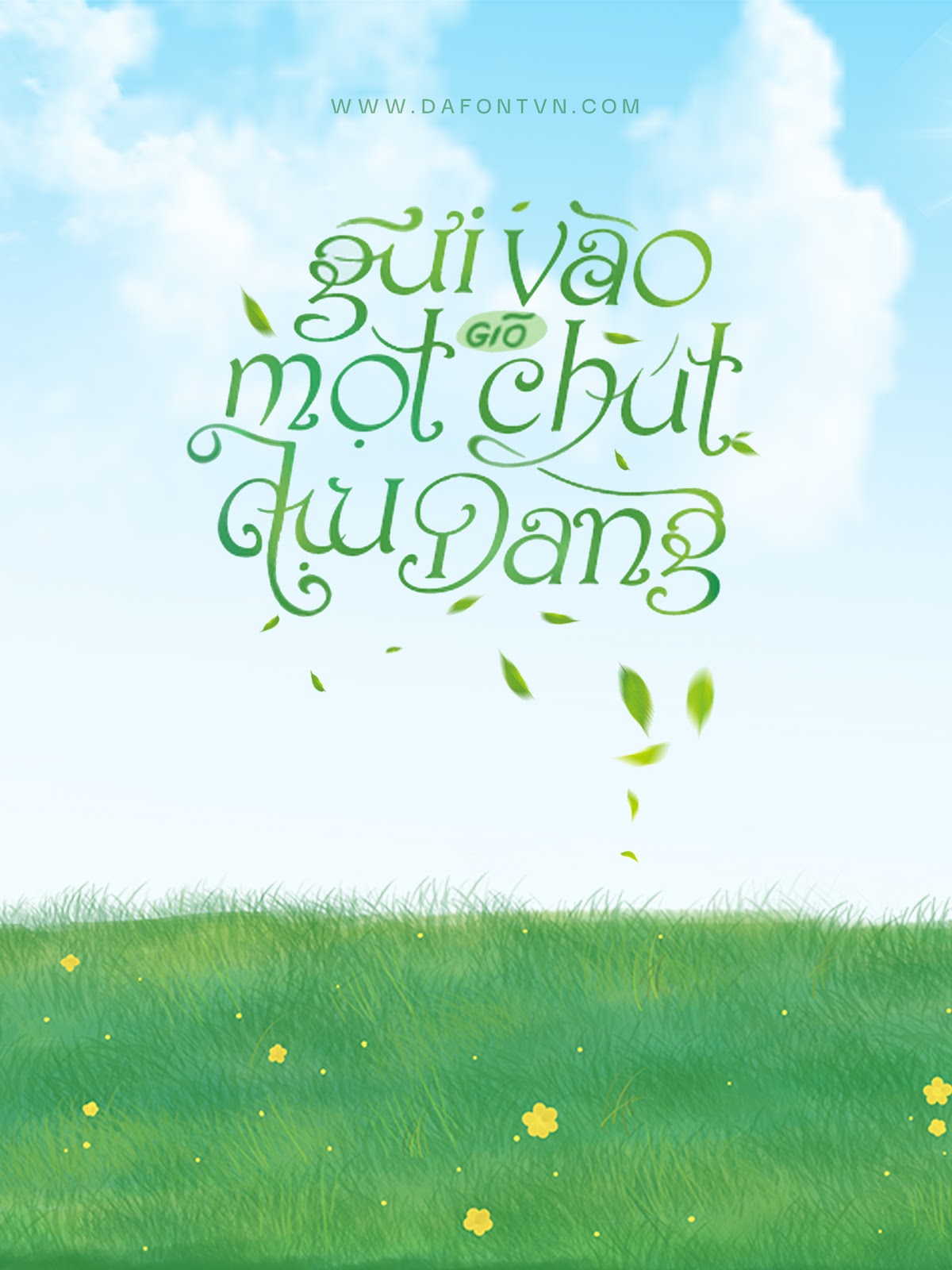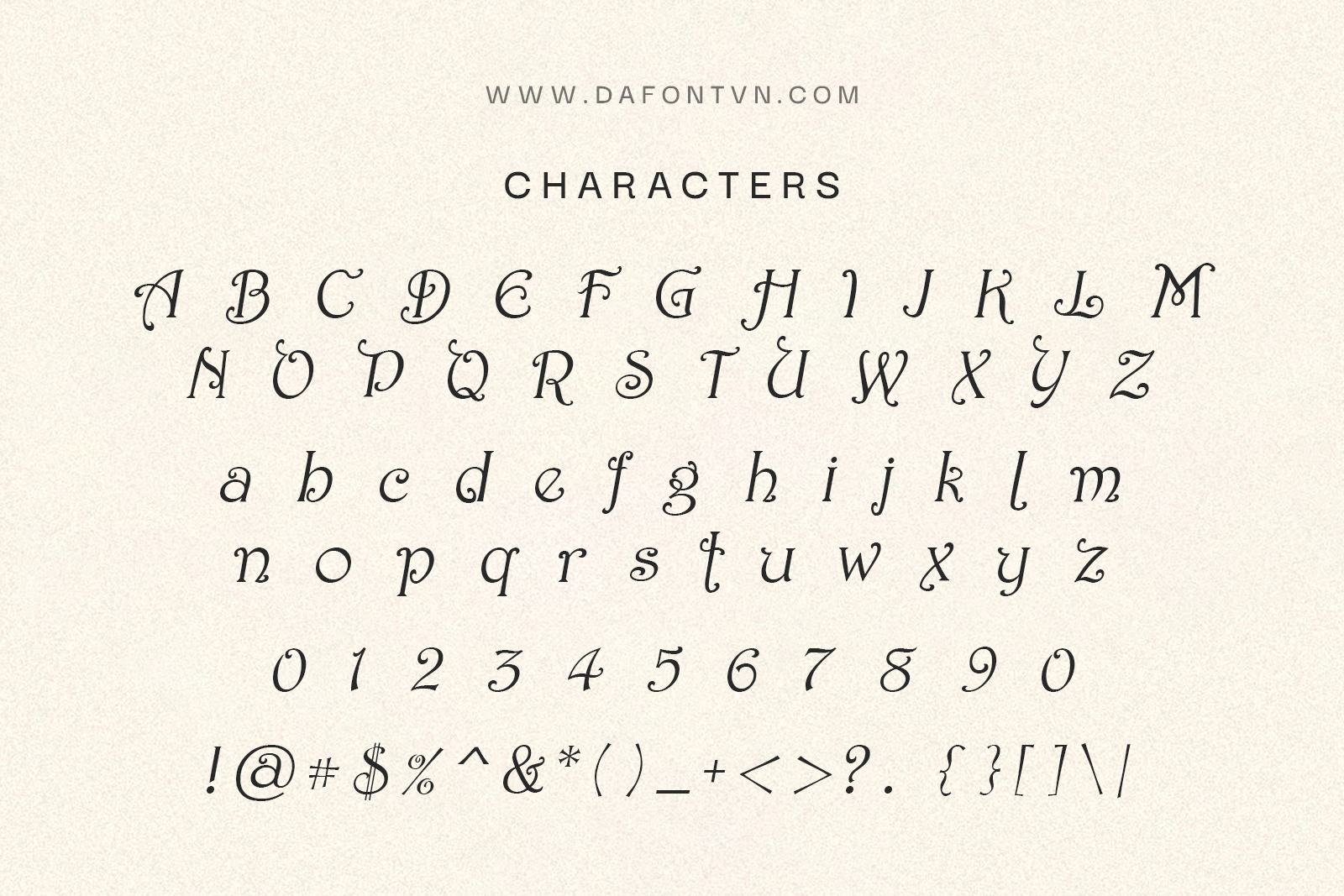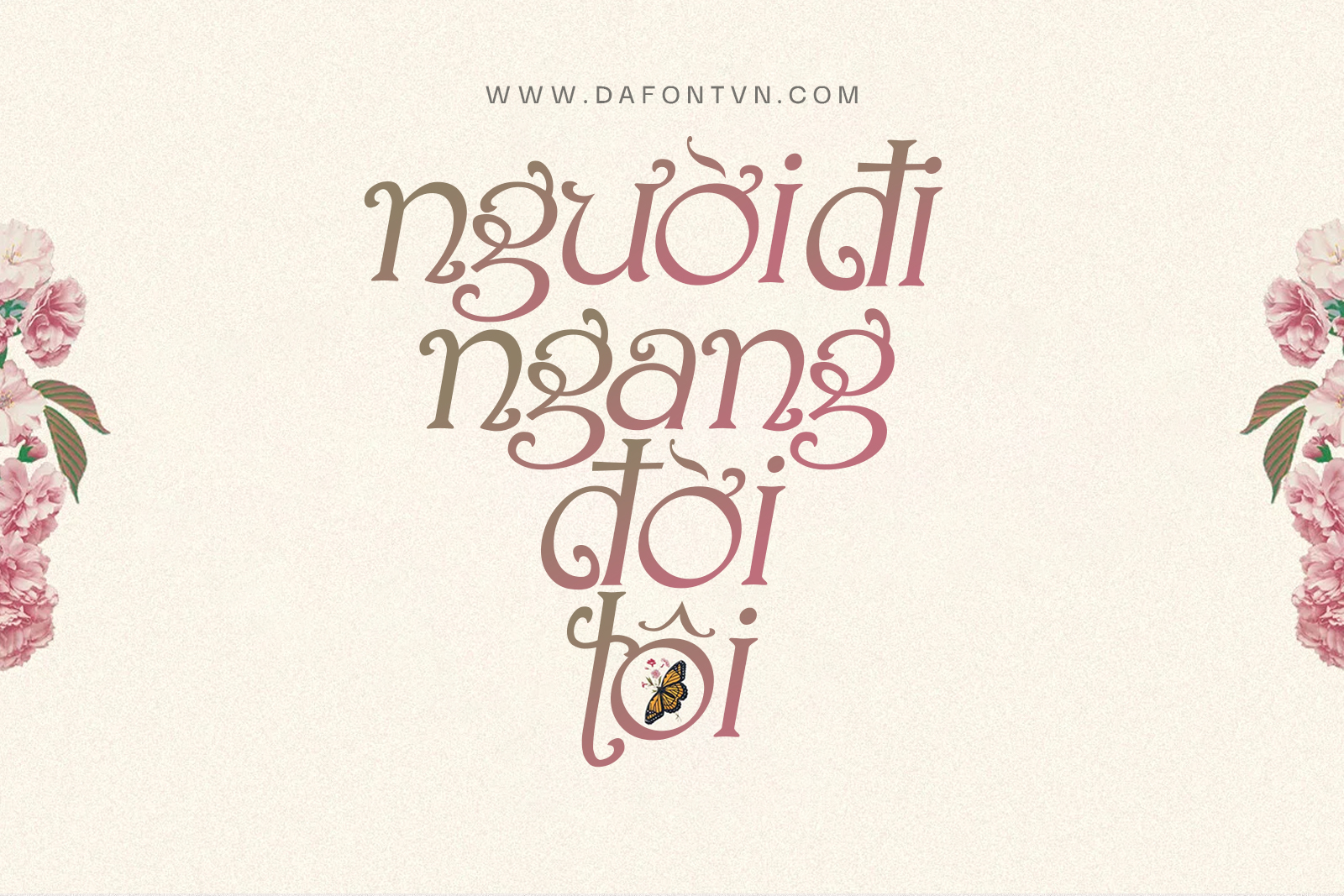
Alvens font là một kiểu phông chữ hiển thị rất xinh đẹp và phong cách. Mặc dù không có nhiều glyph đi kèm nhưng với các đường nét khá ấn tượng của font sẽ giúp bạn tạo ra các tác phẩm hoàn hảo. Font phù hợp với nhiều thiết kế khác nhau chẳng hạn như làm bìa sách, typography, thời trang, tạp chí…
Font Alvens việt hóa đầy đủ, kerning lại, mã hóa PUA và các dấu tiếng Việt được vẽ lại hoàn toàn rất đẹp luôn nhé.